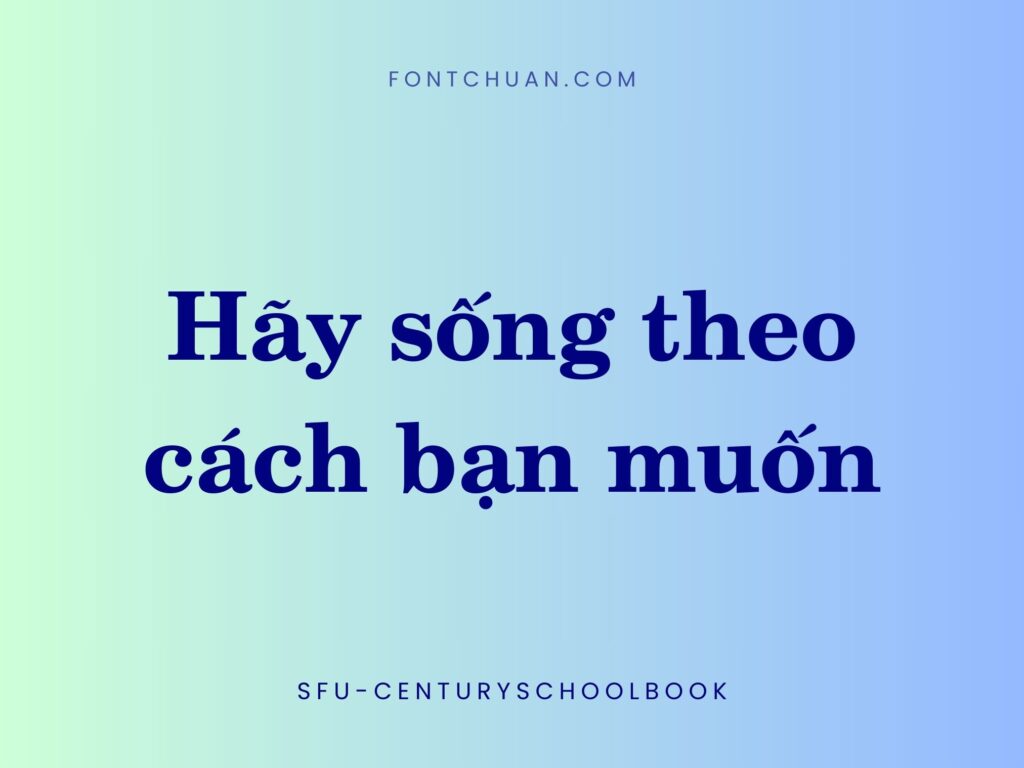
Font Century Schoolbook là một kiểu chữ serif chuyển tiếp, được thiết kế bởi Morris Fuller Benton vào năm 1919 cho American Type Founders theo yêu cầu của nhà xuất bản sách giáo khoa Ginn & Company. Với mục tiêu tạo ra một kiểu chữ dễ đọc cho sách giáo khoa, Century Schoolbook mang lại cảm giác hoài cổ và thân thiện, phù hợp cho nhiều mục đích thiết kế khác nhau như in ấn, xuất bản và thiết kế kỹ thuật số. Font này hỗ trợ đầy đủ tiếng Việt, giúp người dùng dễ dàng ứng dụng trong các dự án đa ngôn ngữ
Về đặc điểm thiết kế, Century Schoolbook có các nét chữ tròn trịa, mở rộng và vững chắc, mặc dù có vẻ nặng nề hơn so với nhiều font serif khác, nhưng nó đứng đầu trong danh sách các font chữ dễ đọc và chịu được nhiều áp lực. Kiểu chữ này rất phù hợp để sử dụng trong các thiết kế như sách, tạp chí, thiệp mời, logo và các ấn phẩm quảng cáo
Font Century Schoolbook được ứng dụng rộng rãi trong các sự kiện như lễ hội, ngày Nhà giáo, Giáng sinh, Halloween, Tết. Nó phù hợp với nhiều ngành nghề như quảng cáo, giáo dục, công nghệ, bất động sản, ẩm thực